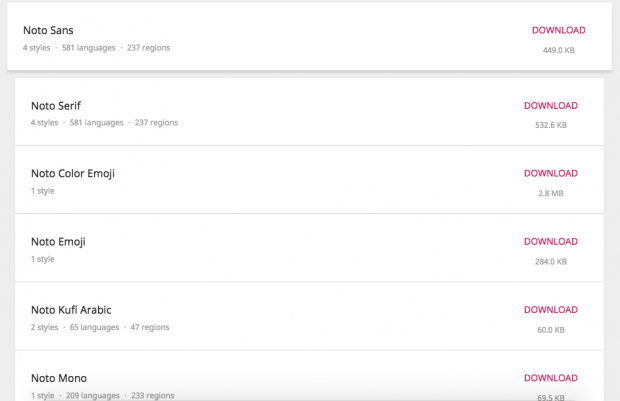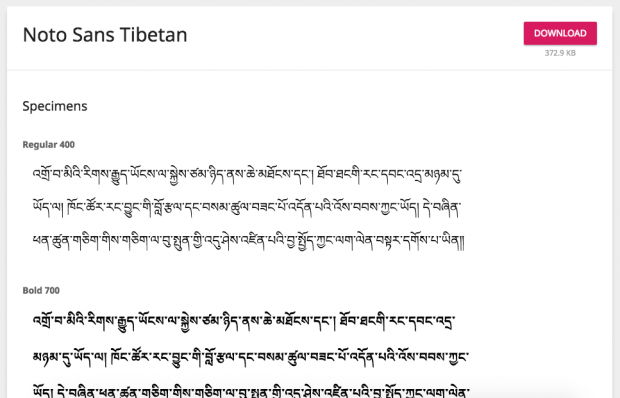
Mời tải về Google Noto, bộ font chữ toàn cầu hỗ trợ hơn 800 ngôn ngữ
Có bao giờ bạn gặp những đoạn văn bản bằng những ngôn ngữ lạ, máy tính không có font hỗ trợ và bạn chỉ thấy những ô vuông hiện ra thay cho ký tự không?
Những ô vuông đó được gọi là 'đậu hũ' (tofu), vì trông chúng giống miếng đậu hũ thật. Đó là lý do hãng Google giới thiệu bộ font mới mang tên Google Noto (nghĩa là 'No tofu', không còn 'đậu hũ' nữa). Bộ font Noto này là kết quả của sự hợp tác giữa Google và Monotype, công ty thiết kế chuyên về các dạng font chữ.
Được phát triển trong 5 năm qua, đến nay bộ font Google Noto đã hỗ trợ đến hơn 800 ngôn ngữ khác nhau, cùng 100 kiểu viết ký tự (bao gồm các emoji và biểu tượng).
Theo Monotype, họ chọn hợp tác cùng Google để giúp việc giao tiếp toàn thế giới vượt qua các rào cản biên giới, ngôn ngữ và văn hoá. Và thực sự như vậy, đây có thể coi là bộ font toàn cầu, hỗ trợ những ngôn ngữ mà chưa có font nào trước đó làm được. Ví dụ, Google và Monotype đã thực hiện một cuộc nghiên cứu chuyên sâu tại các thư viện để tìm hiểu cách viết ngôn ngữ Tây Tạng, và làm việc cùng một tu viện tại Tây Tạng để hoàn chỉnh bộ font Noto Tibetan cho tiếng Tây Tạng.
Bộ font Google Noto tiếng Tây Tạng
Hiện dự án này vẫn còn đang tiếp tục khi Google và Monotype vẫn đang làm việc với các nhà thiết kế và chuyên gia ngôn ngữ để bổ sung thêm ngôn ngữ và biểu tượng hỗ trợ cho bộ font Google Noto.